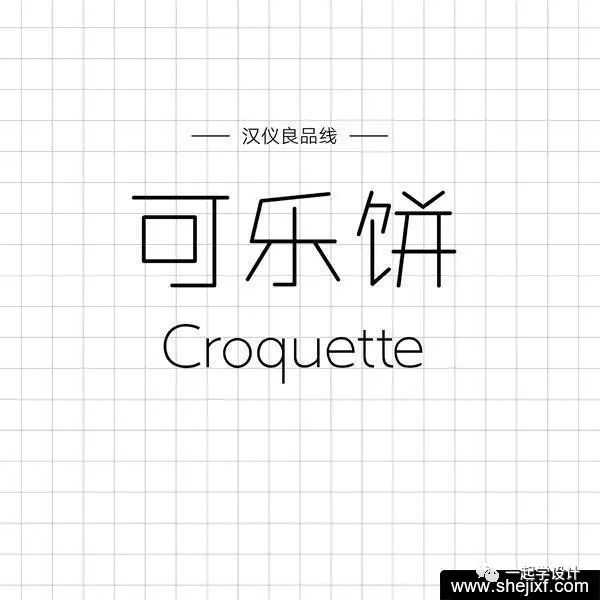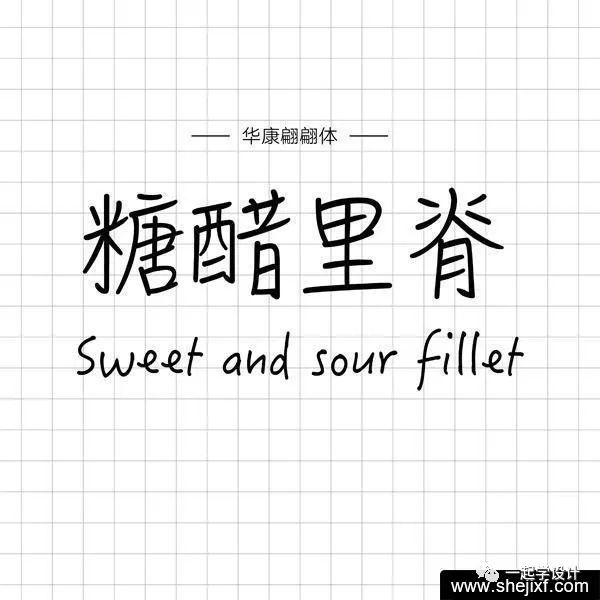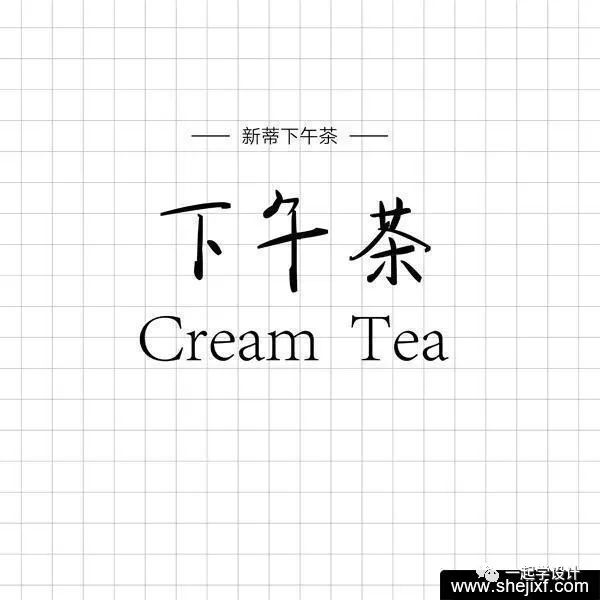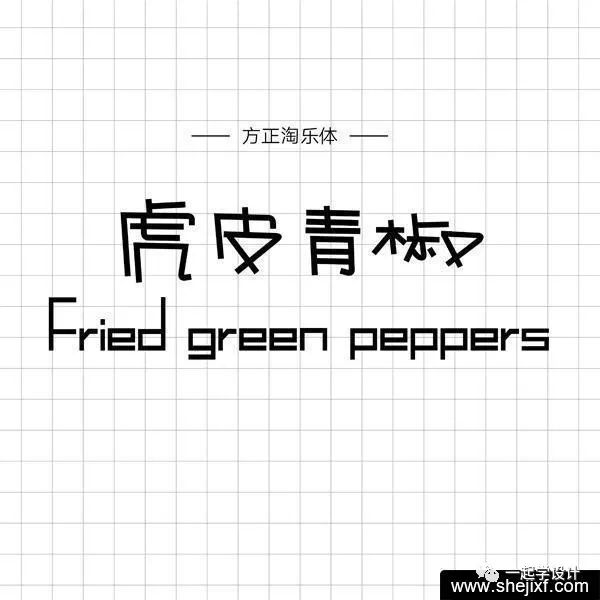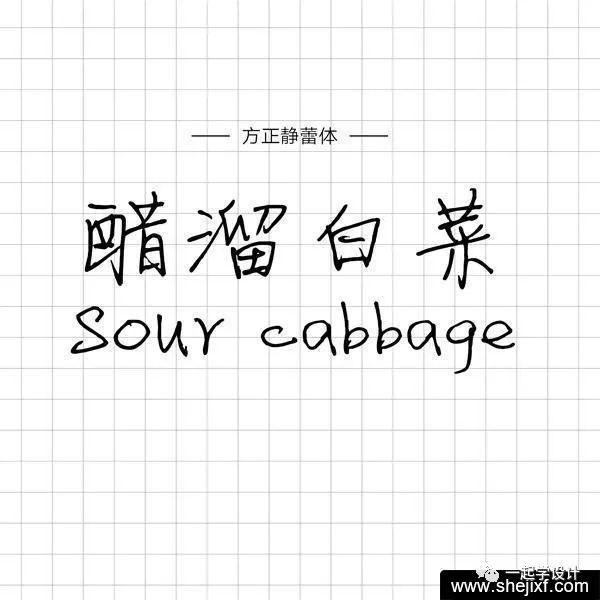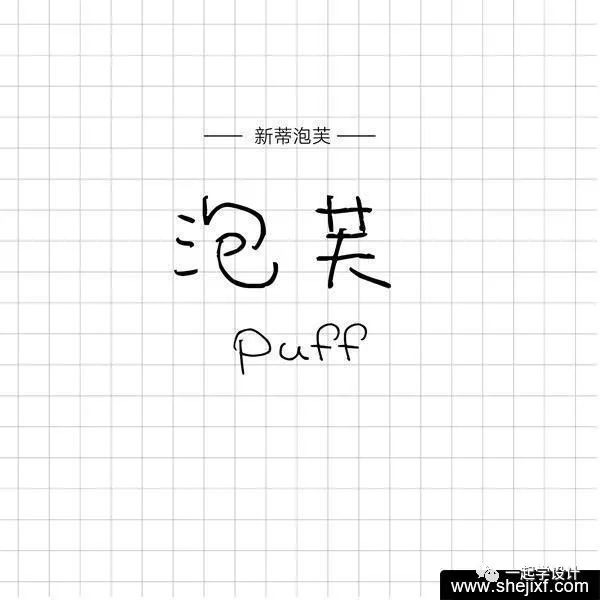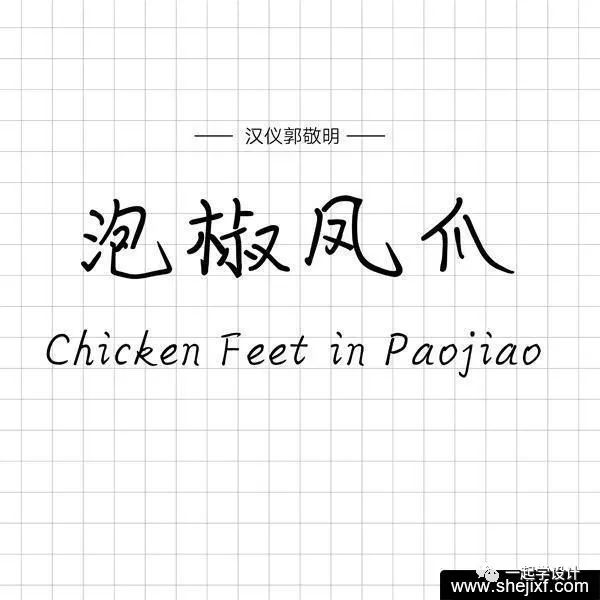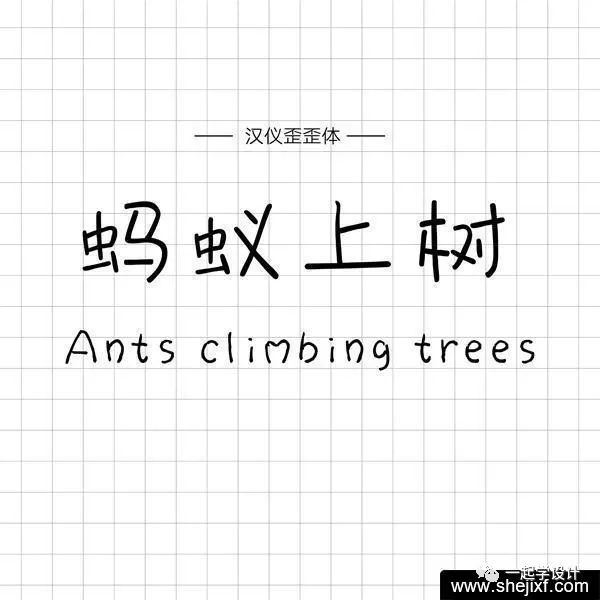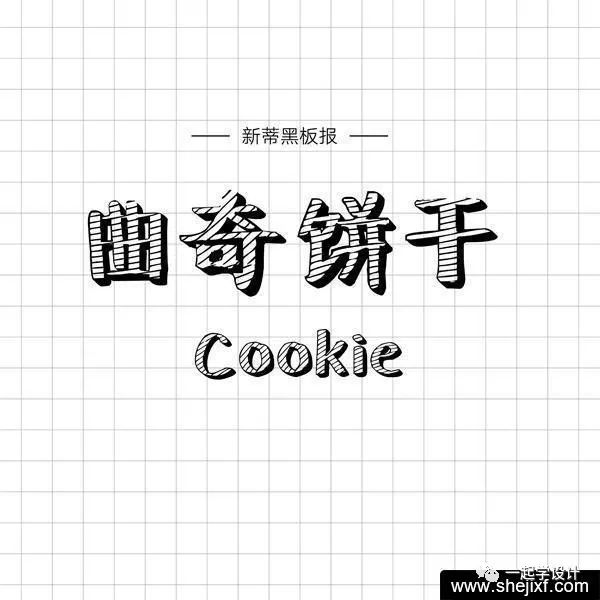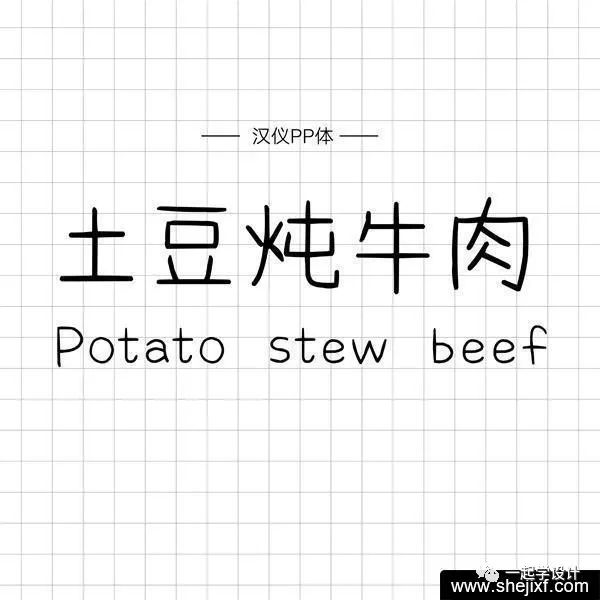
大家在设计中经常会用到手写字体,手写字体不仅能增加设计感同时还能增加画面的活跃度,让用户感到更亲切。特别在一些插画作品中使用得更加广泛。今天一起学设计小编给大家分享12款经典的手写字体。
是不是觉得特别温暖,特有人情味儿。这些字体用在设计中,都会为你的设计增添不少'人情味',更带给人亲切的感觉。
下面就由小编介绍几款优质的手写字体给大家:
01
标题党级别字体
标题党级别的含义就是:作为标题字体最重要的就是'引人注目',所以线条一定不能太细啦,粗壮的线条或者变换多端的造型,都有着强大的表现力,这让看官的眼睛,想挪都挪不开!
汉仪黑荔枝体
方正咆哮体
方正喵呜体
方正淘乐体
新蒂黑板报
汉仪小麦体
汉仪乐喵体
02
优雅小标签字体
小标签是最朴实无华的存在,任何地方都需要,写名字、标价包括最简单的对话,清晰又温暖。不过这里面提到的两位名人'井柏然'和'郭敬明'到目前为止,只能在手机QQ上用到,两位的粉丝们还是可以在QQ上过把瘾的。
汉仪柏京体
汉仪悠然体
汉仪PP体
汉仪寒石体
汉仪井柏然体
华康偏偏体
新蒂小丸子
汉仪时光体
汉仪郭敬明体
03
精致小标题字体
这些字体的相对上面两个级别的稍微细一些,但也是做小标题的好手,细线条更精致,徐老师的精致的静蕾体可谓是红了数十年,这里为大家呈现更多的选择,毕竟'文字复兴'也可'百家争鸣'啦。
汉仪歪歪体
造字工房情书
汉仪良品线
汉仪伊宁隶
汉仪平安行
方正静蕾体
方正寂地体
新蒂泡芙
新蒂绿豆汤
新蒂下午茶